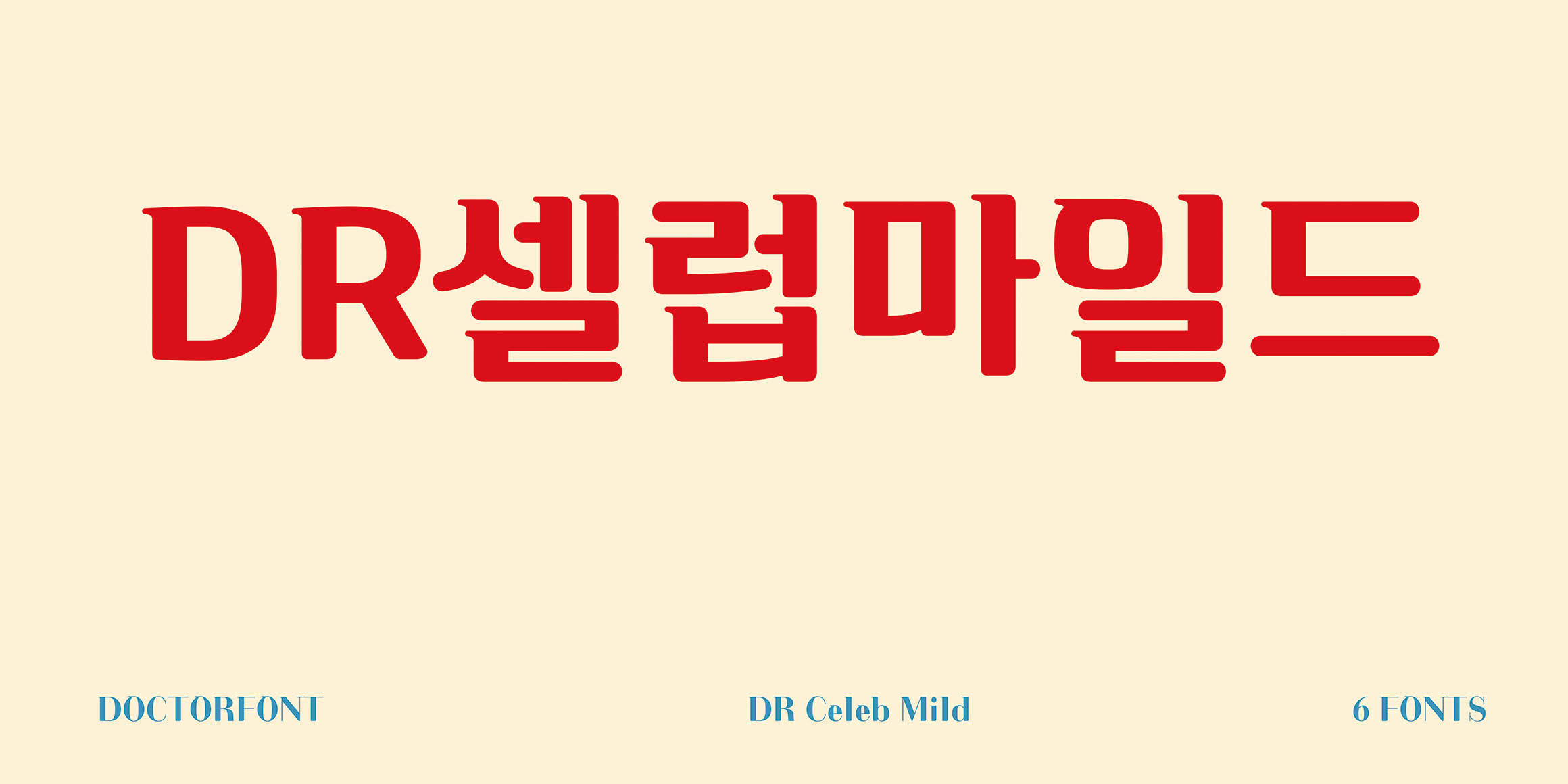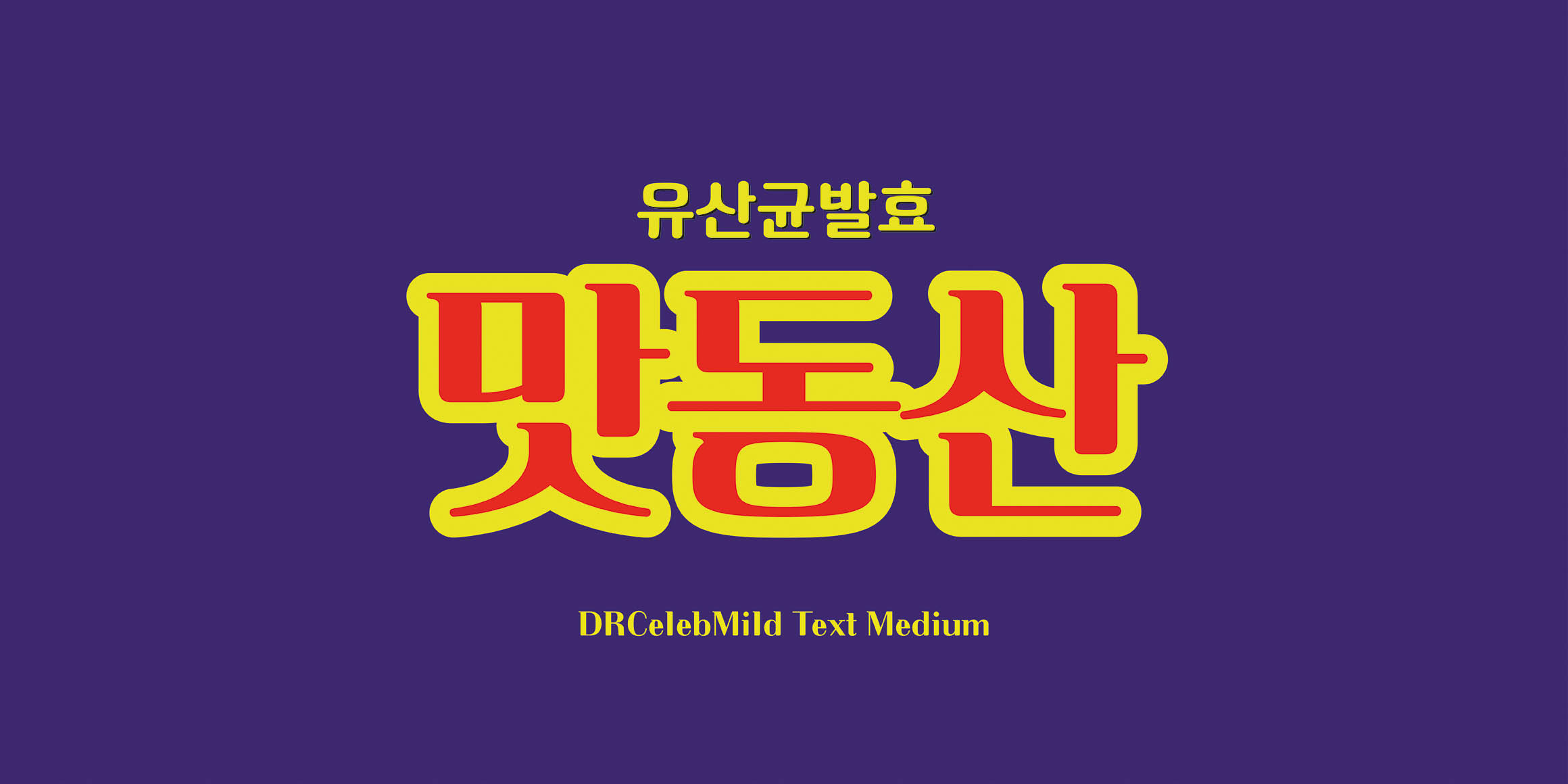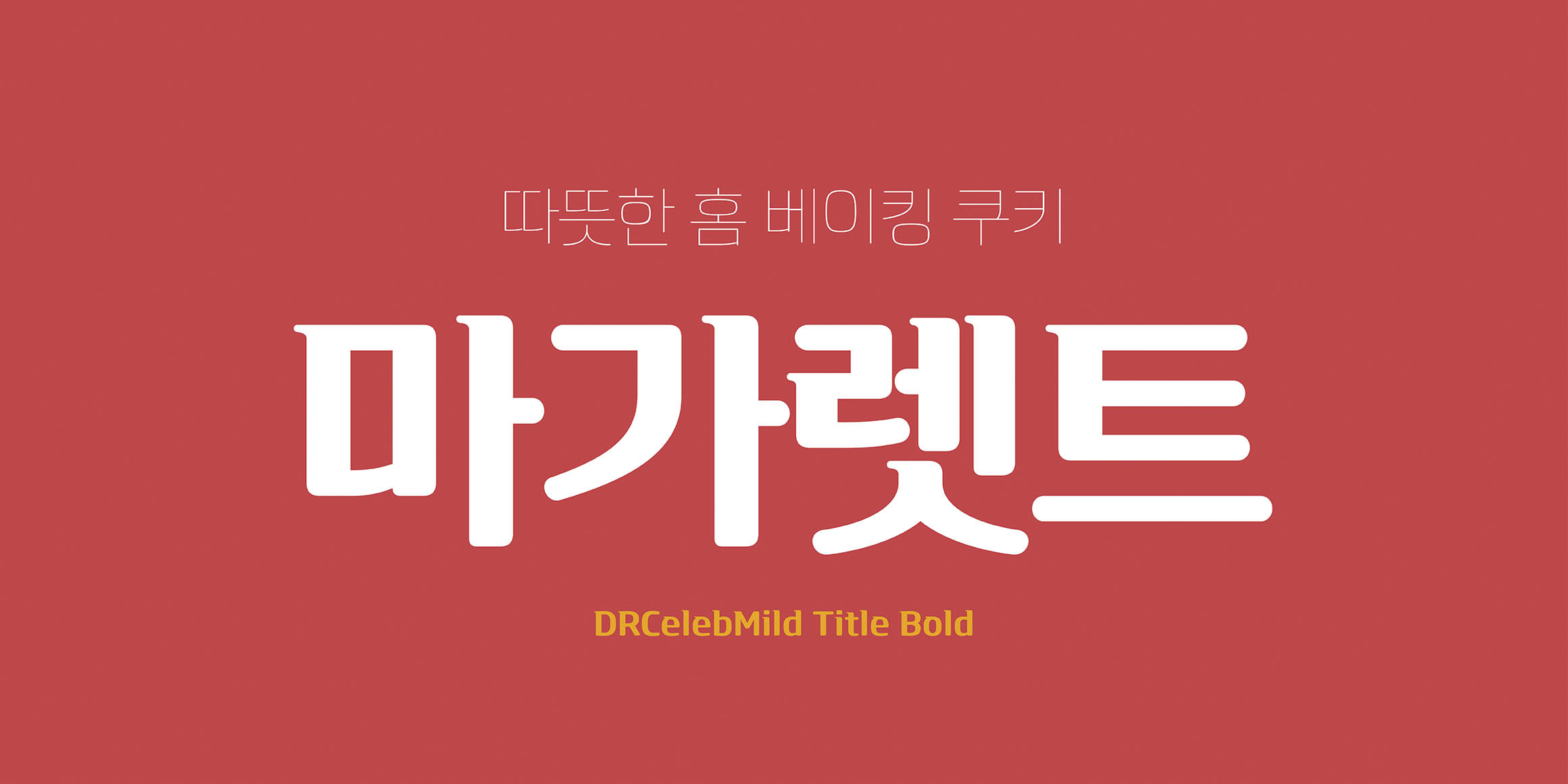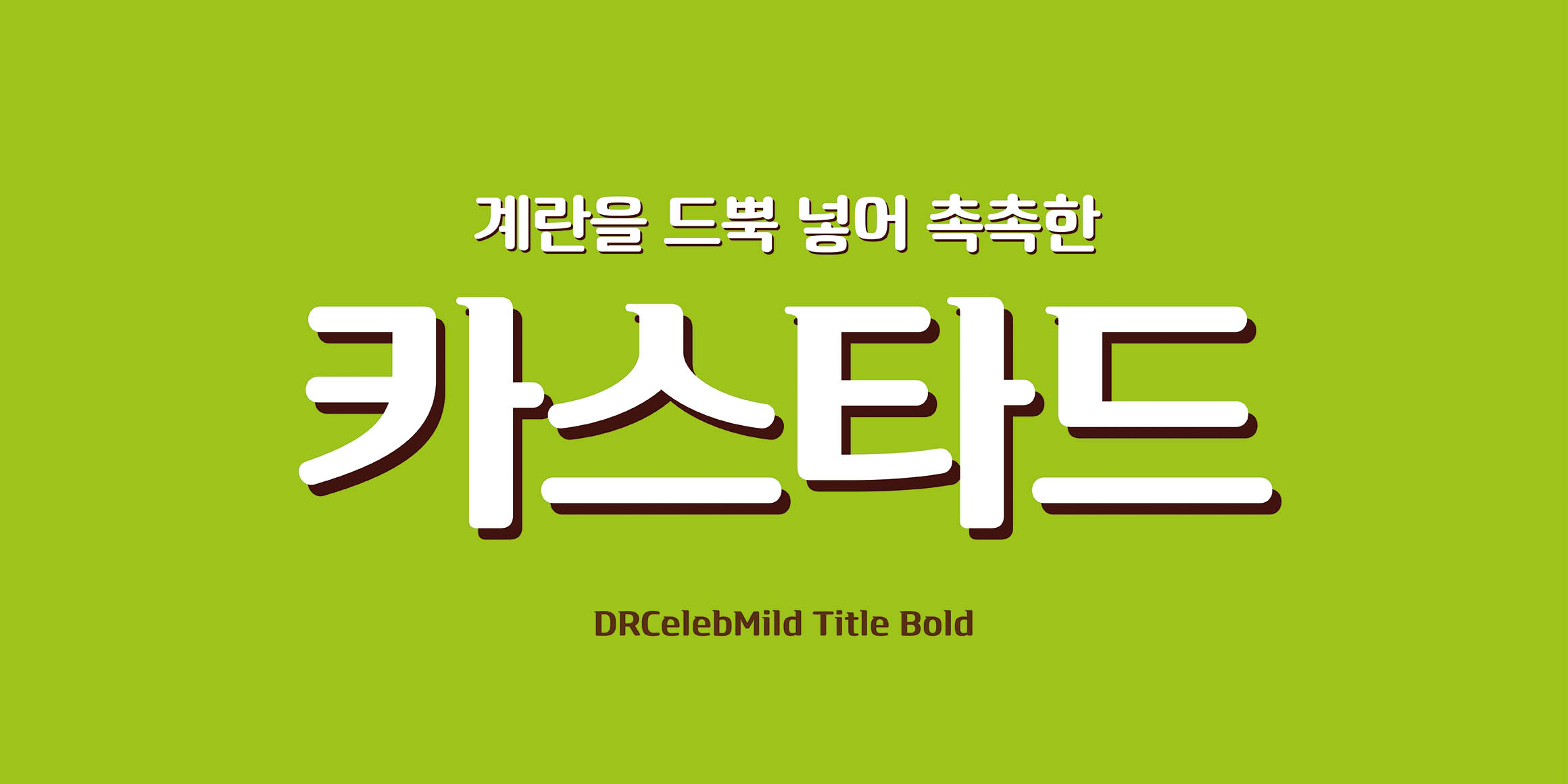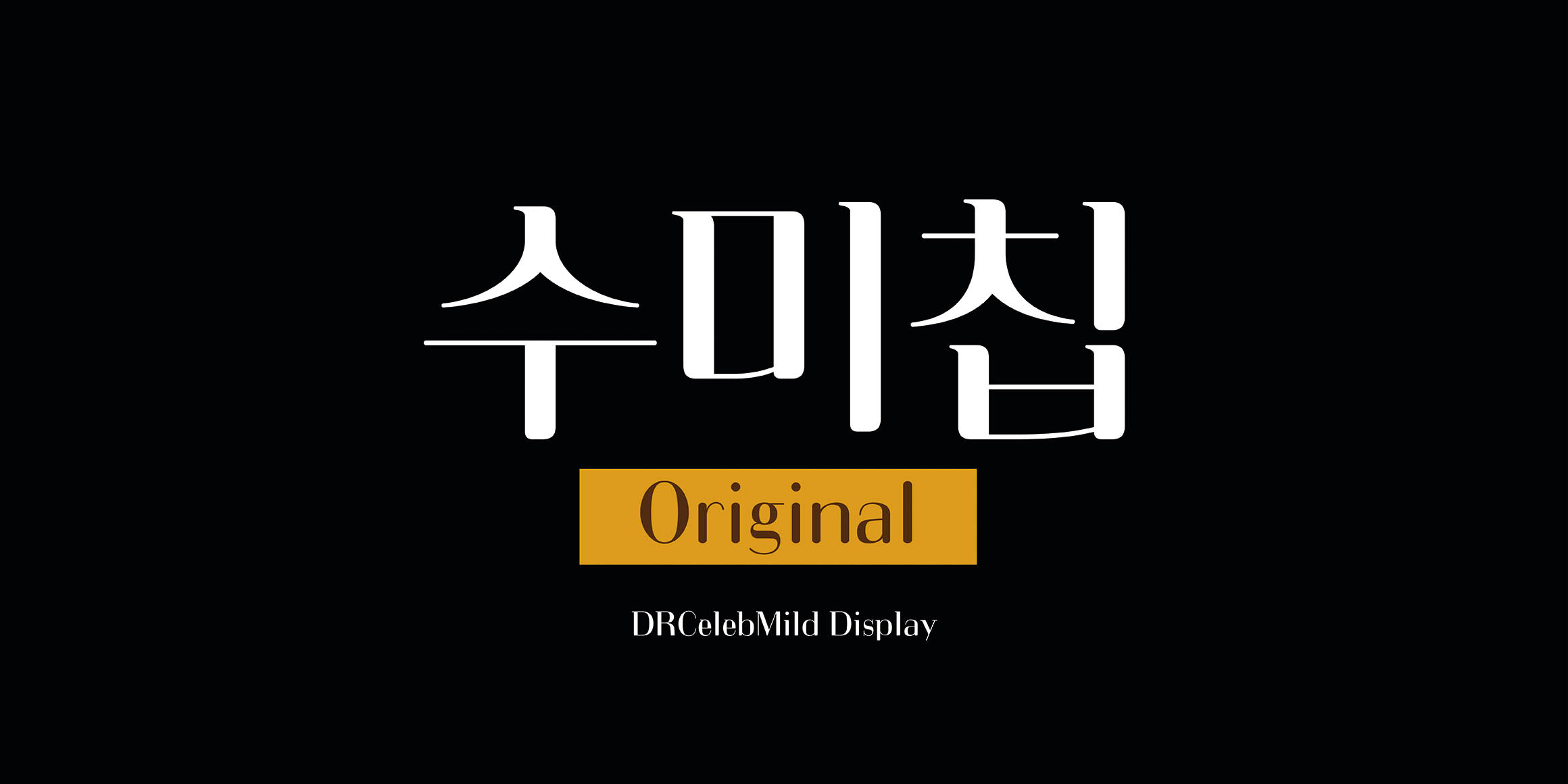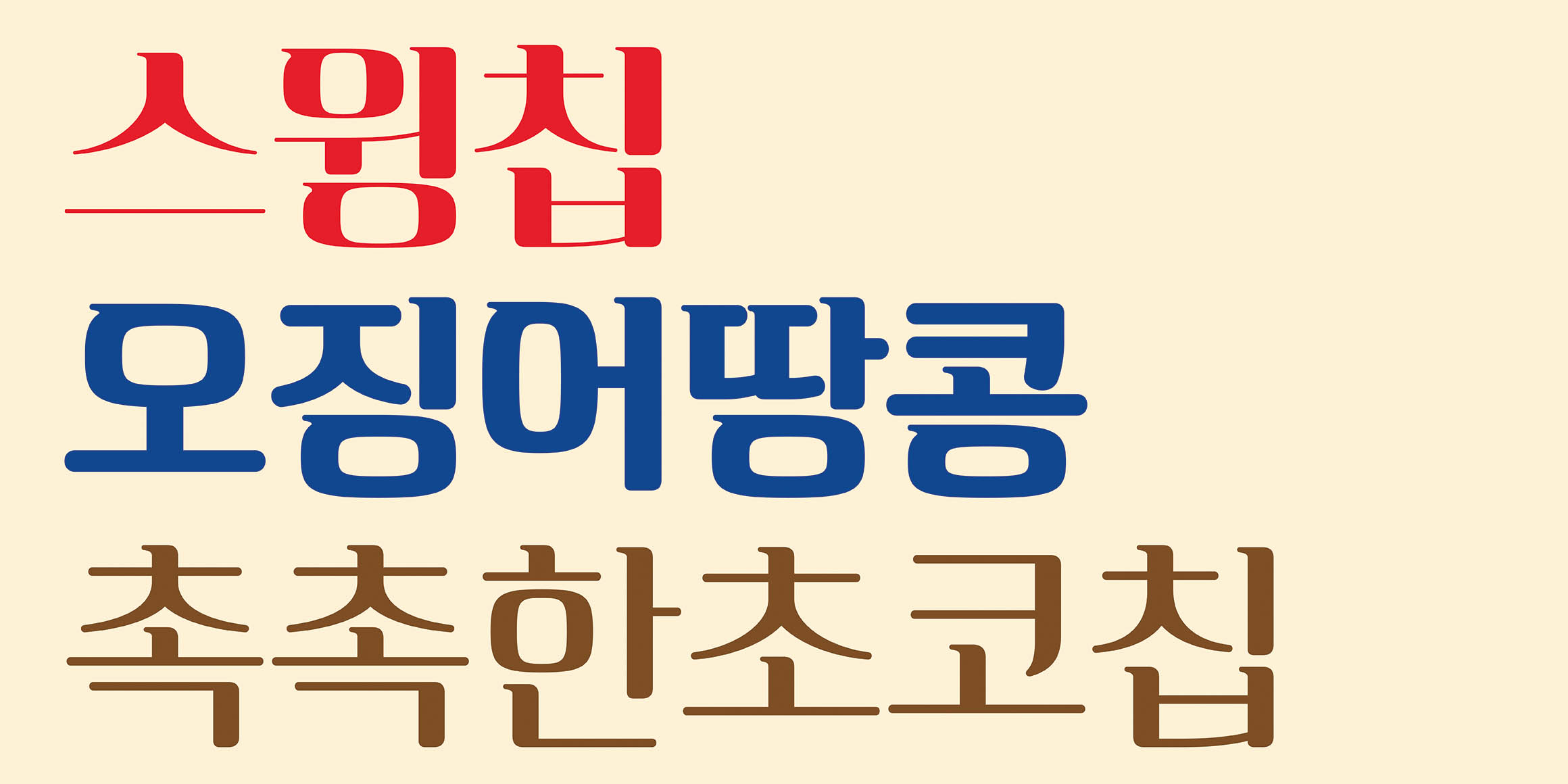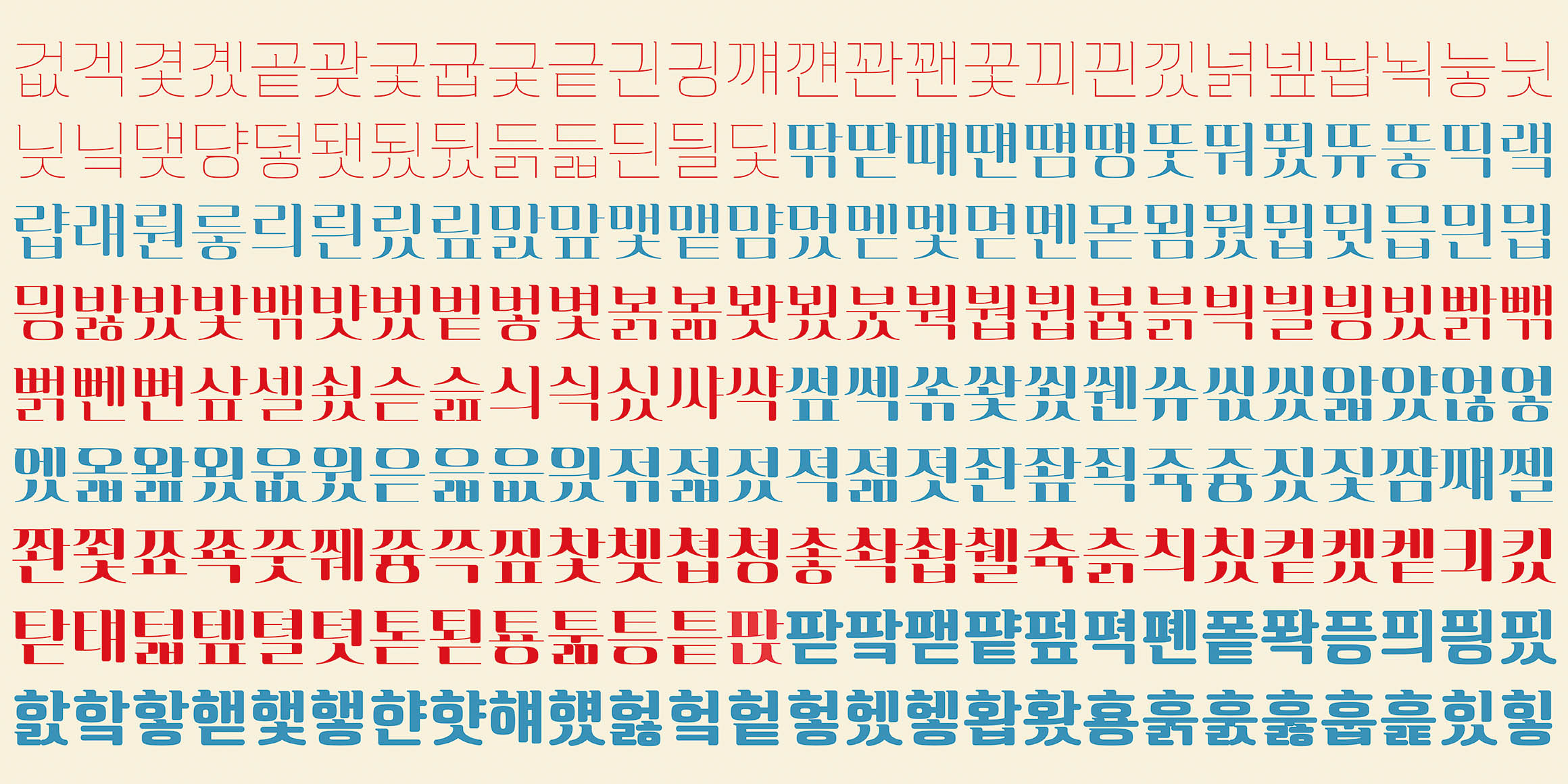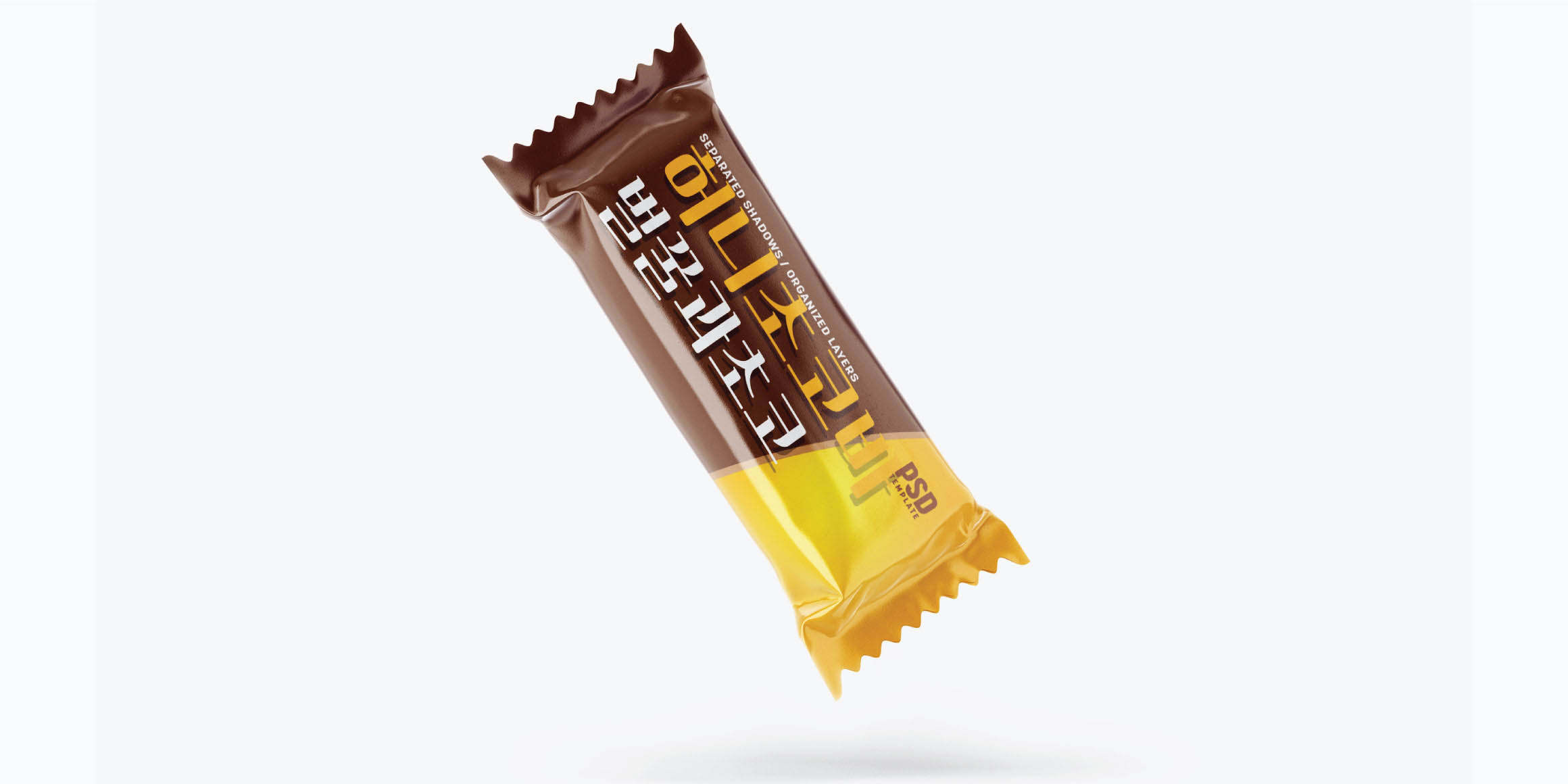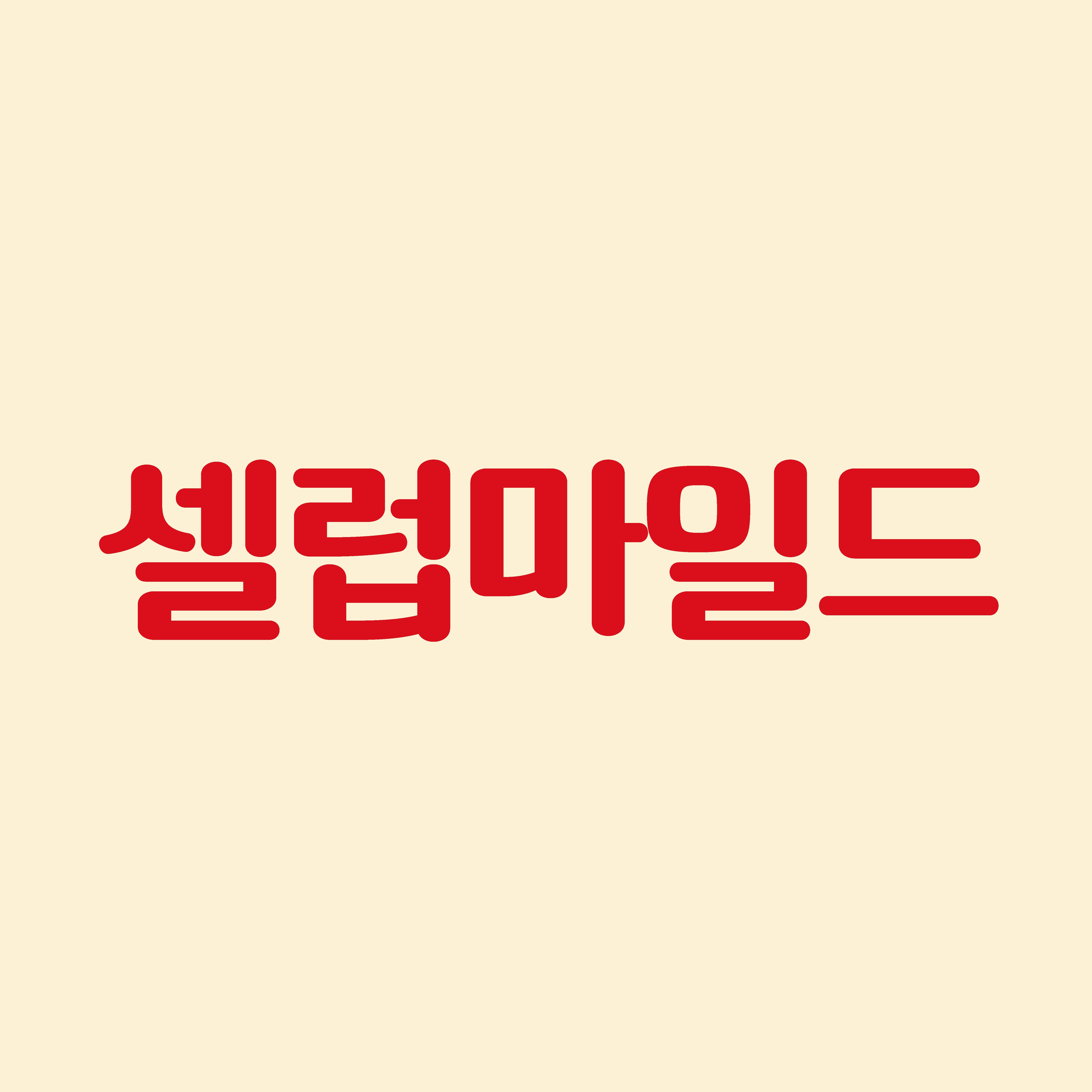
DR셀럽 마일드
셀럽마일드는 자소의 모서리부분에 작은 라운드를 주어 기본 형태와 부드러움을 함께 표현하고 있고 부드러운 세리프에서는 부드러운 주목성을 강조하고 있습니다. 형태적으로 ‘ㅇ’에도 세리프를 표현한 것이 특징이라 할 수 있습니다. 모두 6개의 패밀리로 개발되었고 식품패키지나 먹방 유튜브 타이틀 등에 잘 어울립니다.